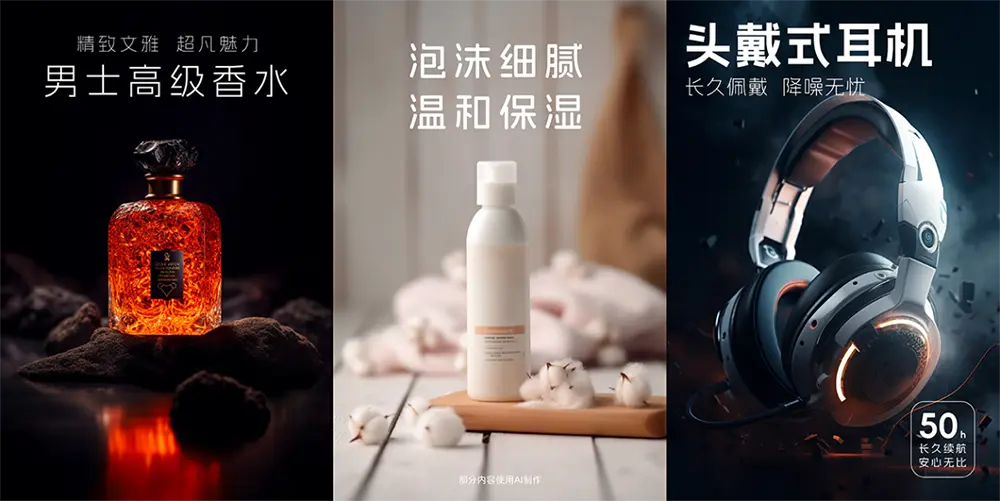
阿里媽媽方圓體為一款簡體中文雙軸可變字體,收納的中文字符包括但不限於GB2312,共計6763個漢字;英文大小寫共52個;常用標點符號共227個,總計7042個字符
設計說明:通過智能 AI 的方式在20天內完成的這款字,是目前國內外為數不多的中文雙軸可變字體。方體堅實而硬朗,圓體潤澤而柔美;方圓間的切換讓方圓體極具適用性,也解放了創意表達的更多可能性。粗細的可變使得設計師具備無限微調的可能,讓創意設計有了豐富表達。